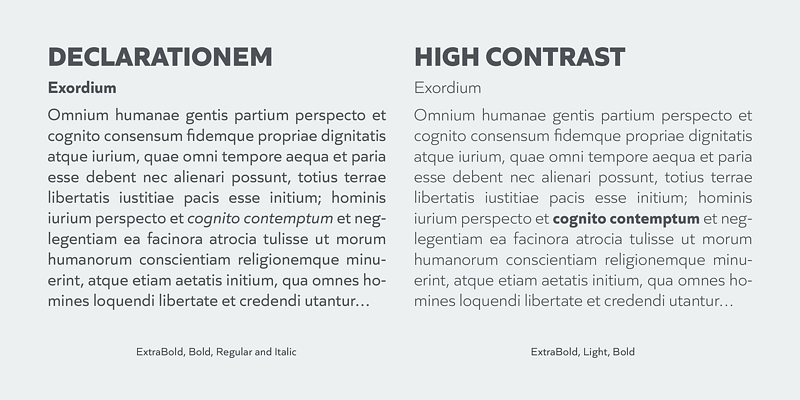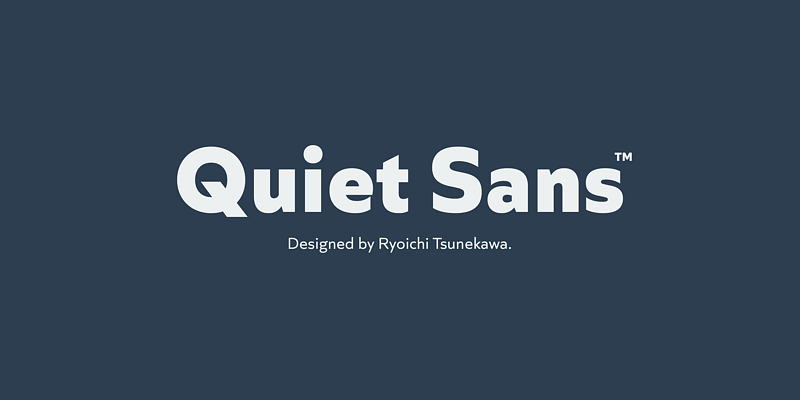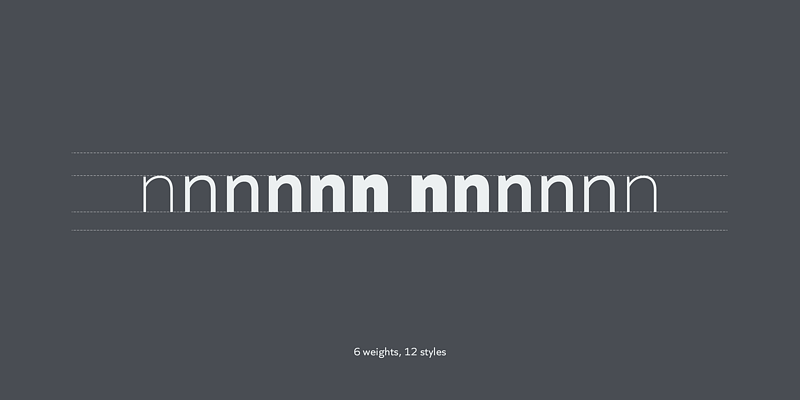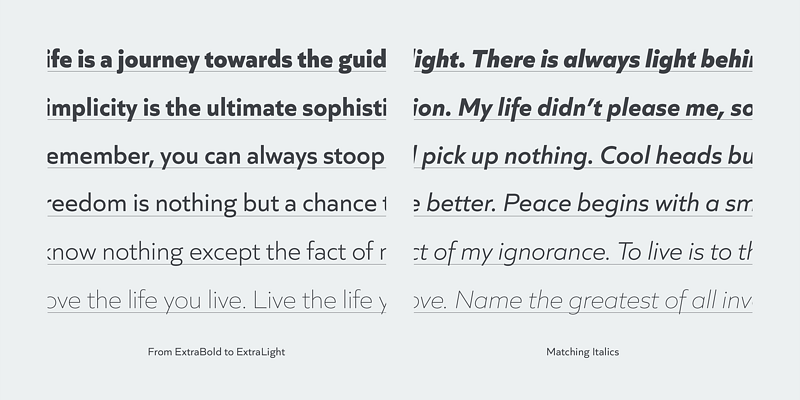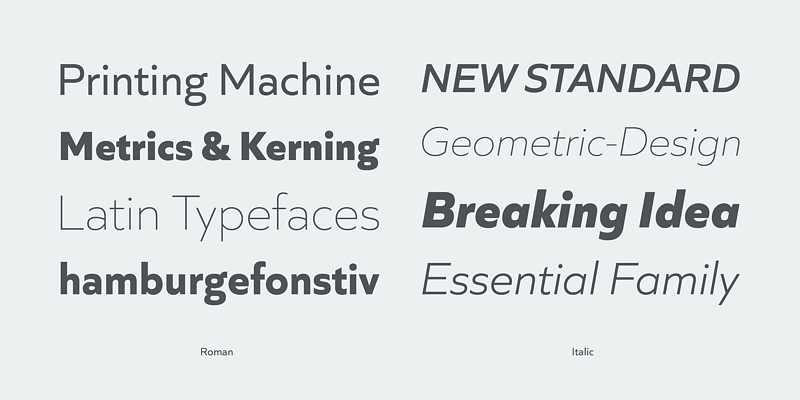
Quiet Sans è un sans serif super geometrico. Il concetto alla base di questa famiglia non è solo quello di lasciare il segno, ma anche quello di essere leggibile anche su schermi di piccole dimensioni.